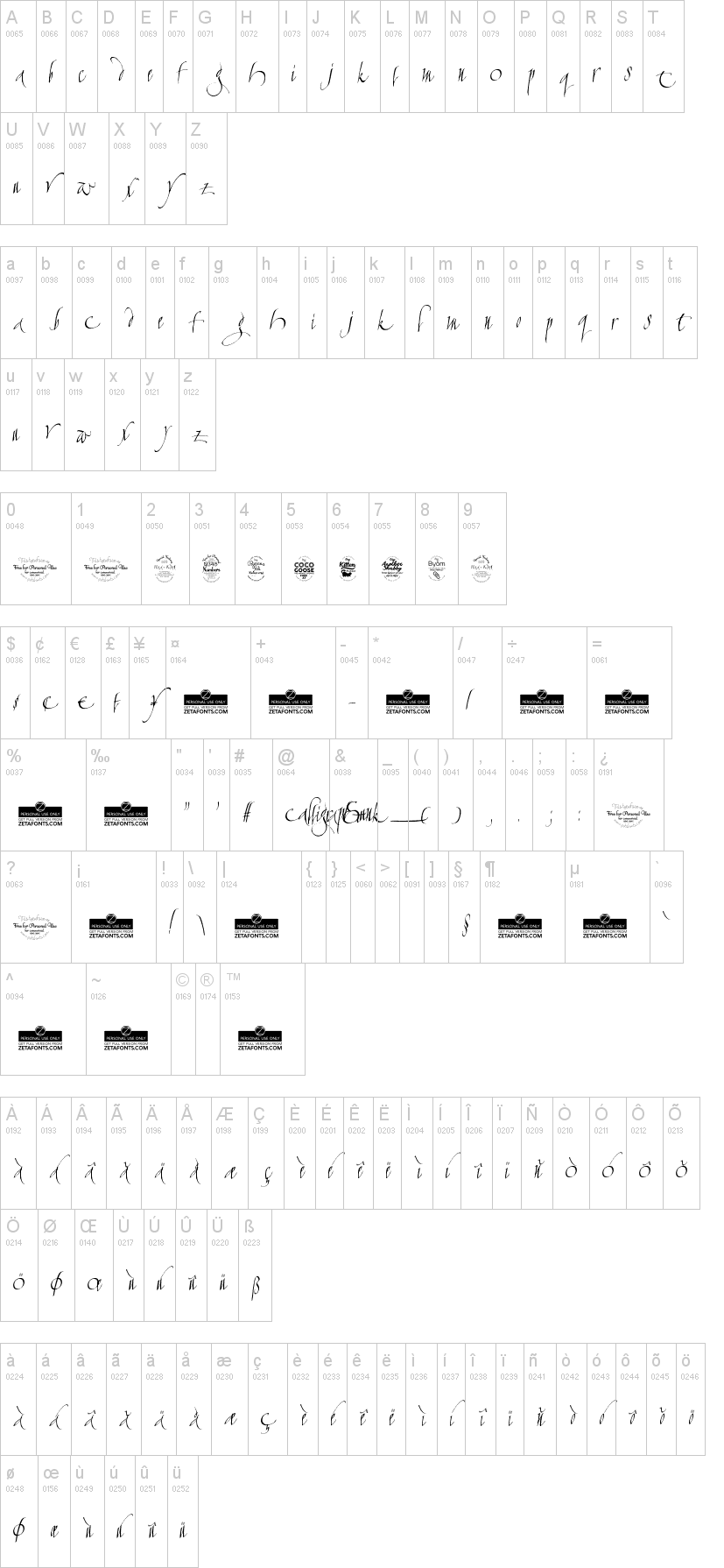
Calligraphunk
Calligraphunk 是一种手写风格的字体,它融合了书法和涂鸦的元素,给人一种独特的感觉。该字体的笔画流畅,线条粗细不一,有些地方甚至有点凌乱,但这些特点正是该字体的魅力所在。 Calligraphunk 字体的风格比较随意,适合用来设计一些个性化的宣传海报、商标、书籍封面等等。该字体还带有一些涂鸦的元素,使得它看起来比较时尚和年轻化,受到很多设计师的喜爱。此外,该字体也适合用在一些大型活动的宣传中,如音乐会、时装秀等等,让你的宣传更加突出和引人注目。 总的来说,Calligraphunk 字体是一种非常有个性和时尚感的字体,它能够增加你的设计作品的独特性和吸引力。
Calligraphunk是一款非常不错的手写艺术字体,具有很好的视觉感,适合于文化类的宣传设计、商业类品牌的广告和产品包装设计以及个性化文字排版等较多场景。